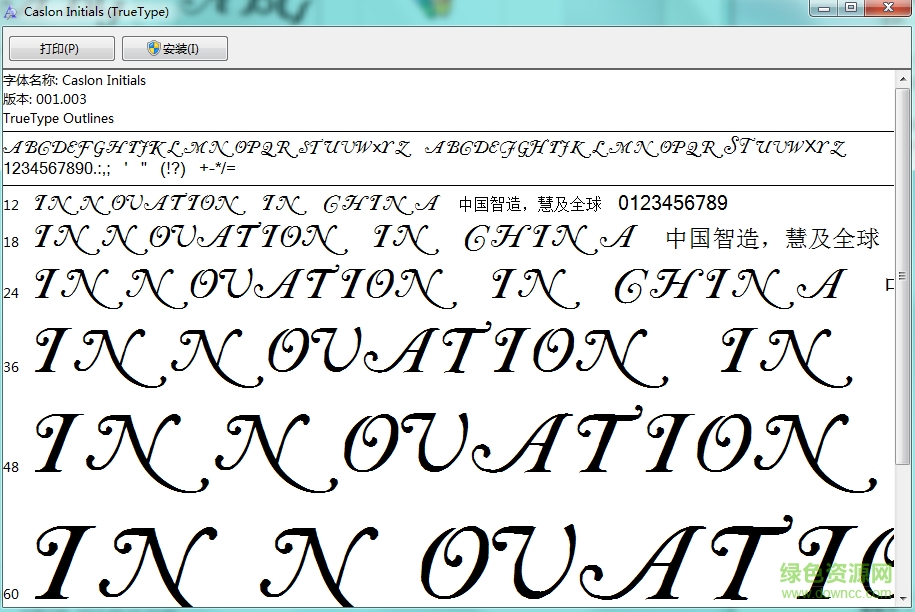
caslon是一款有著不規(guī)則但優(yōu)雅的英文書寫的系列字體,讓你的英文顯得更大氣隨意具有藝術(shù)感,綠色資源網(wǎng)收錄了caslon全套字體,快來下載吧!
Caslon是荷蘭巴洛克風(fēng)格類型的共同違規(guī)設(shè)置的serif字體。它的短期上行字母和下行,括號內(nèi)的襯線,是適度的高對比度。斜體有節(jié)奏的書法中風(fēng),和一些小寫的斜體斜的建議。
優(yōu)勢:Caslon有時(shí)被認(rèn)為是一個(gè)偉大的通用字體。甚至還有打印機(jī)和排版人員之間的共同規(guī)則的拇指,“當(dāng)有疑問時(shí),使用Caslon?!边@是一個(gè)多功能的,同樣可用于在標(biāo)題或正文的字體。各種各樣的重量和款式可供使其更加靈活。
最佳用途:Caslon可以用于幾乎任何類型的排版,從體內(nèi)復(fù)制標(biāo)題,和小尺寸是相當(dāng)易讀。